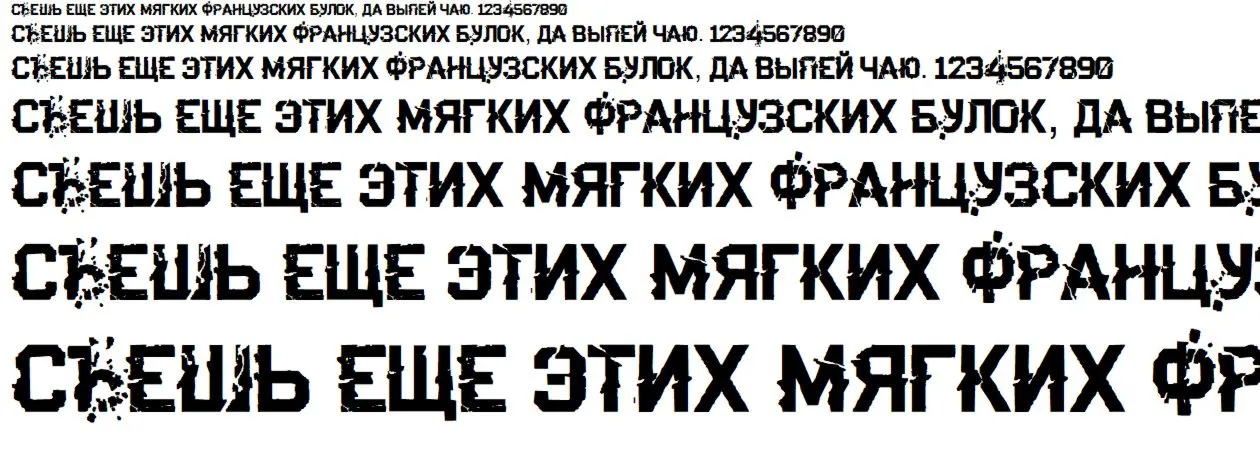
Destroyed Massif — деструктивный дисплейный шрифт с эффектом цифрового глитча и разрушения. Каждая буква выглядит как повреждённый данными артефакт: трещины, пиксельный шум, разрывы контура.
В комплекте: полная кириллица (33 буквы), латиница и цифры (0-9).
Применение: постеры, обложки игр, логотипы, киберпанк-дизайн, хоррор-эстетика, техно-визуал, антиутопии.